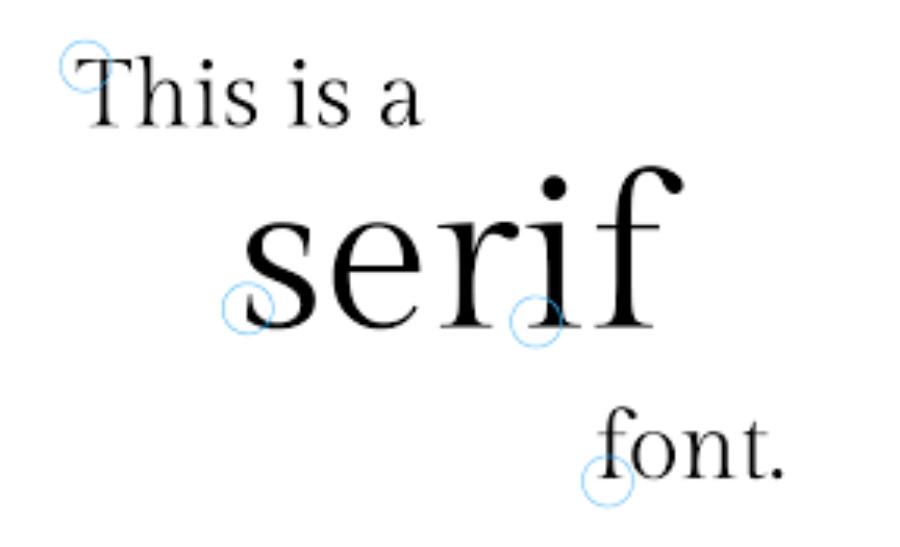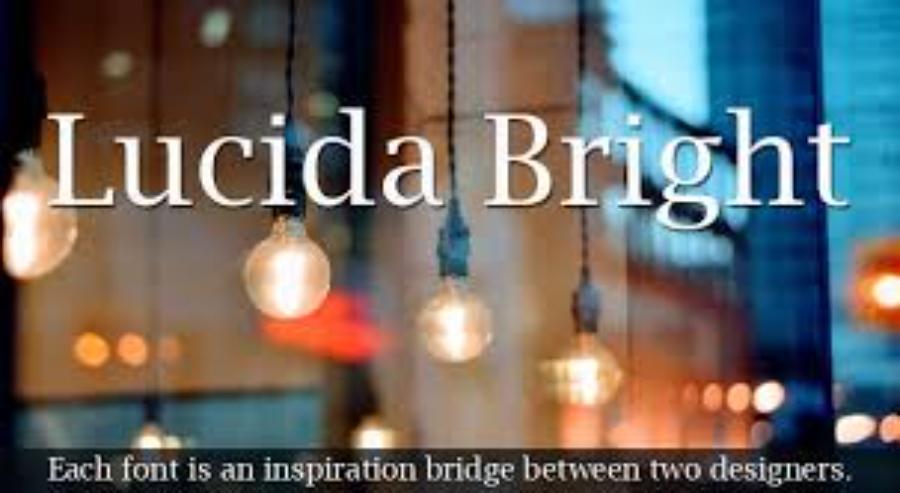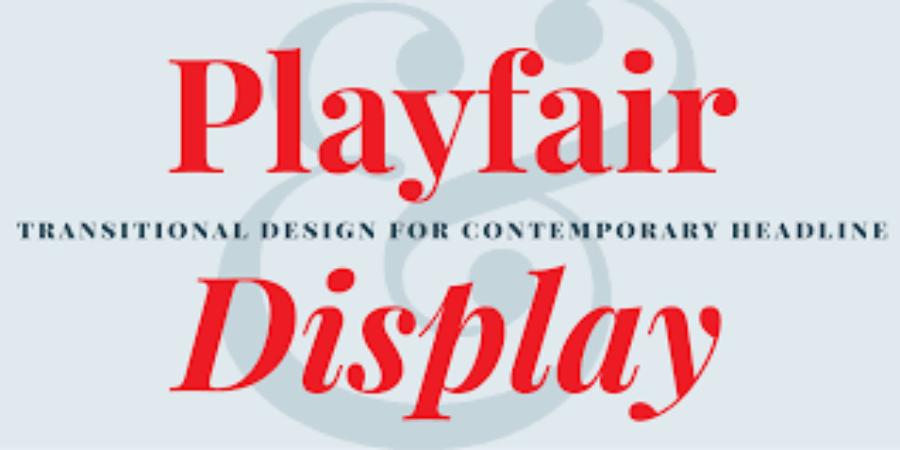
Danh sách 20 Font Chữ Đẳng Cấp Mà Designer Nên Sở Hữu Ngay Hôm Nay
Khám phá 20 fonts chữ sang trọng dành cho designer. Cập nhật bộ sưu tập các font chữ đẳng cấp để nâng tầm thiết kế của bạn, từ phong cách hiện đại đến cổ điển.
Khi thiết kế đồ họa, lựa chọn font chữ đóng vai trò vô cùng quan trọng trong việc tạo ra những ấn phẩm nổi bật. Một font chữ sang trọng không chỉ giúp nâng cao giá trị thẩm mỹ mà còn thể hiện được sự chuyên nghiệp và tinh tế của nhà thiết kế. Trong bài viết này, sadesign sẽ giới thiệu 20 fonts chữ sang trọng mà mọi designer đều nên có trong bộ sưu tập của mình, giúp các bạn dễ dàng lựa chọn những kiểu chữ phù hợp với từng dự án.
1. Serif - Một Biểu Tượng Của Sự Sang Trọng
Serif là một trong những loại font chữ cổ điển và thường xuyên xuất hiện trong các thiết kế mang tính trang trọng. Với các chân chữ được nối vào phần thân, Serif tạo ra một cảm giác chắc chắn và dễ đọc, đặc biệt phù hợp với những thiết kế cần sự trang nghiêm và lịch sự. Những font như Times New Roman, Georgia, hay Baskerville đều là những ví dụ điển hình cho thể loại này.
Serif luôn được coi là biểu tượng của sự sang trọng và tinh tế trong thiết kế đồ họa. Với đường nét mềm mại, cân đối và đầy tính nghệ thuật, các font chữ Serif không chỉ giúp tăng tính thẩm mỹ mà còn mang lại cảm giác chuyên nghiệp và đẳng cấp cho các dự án thiết kế. Việc lựa chọn đúng font chữ Serif phù hợp có thể tạo nên sự khác biệt lớn, giúp truyền tải thông điệp một cách hiệu quả và gây ấn tượng mạnh mẽ với người xem. Vì vậy, việc khám phá và sử dụng những font chữ sang trọng này là điều mà các nhà thiết kế không nên bỏ qua để nâng tầm giá trị cho sản phẩm của mình.
2. Didot - Sự Tinh Tế Của Font Chữ Sang Trọng
Didot là một font chữ serif nổi bật, nổi bật với các nét thanh mảnh nhưng không kém phần mạnh mẽ. Nó được biết đến với vẻ đẹp thanh lịch và đẳng cấp, lý tưởng cho các thiết kế trong ngành thời trang, làm đẹp, hoặc các sản phẩm cao cấp. Với tỷ lệ tương phản mạnh mẽ giữa các nét chữ, Didot mang đến một phong cách cổ điển nhưng vô cùng hiện đại.
Với sự kết hợp hoàn hảo giữa các đường nét thanh mảnh và độ tương phản cao, Didot mang lại cảm giác hiện đại nhưng vẫn giữ được vẻ cổ điển đặc trưng. Đây là lựa chọn lý tưởng cho các dự án cần thể hiện sự đẳng cấp và tinh tế, từ thiết kế thương hiệu, in ấn cao cấp đến các ấn phẩm thời trang. Sự cân đối trong từng chi tiết của Didot không chỉ tạo ấn tượng mạnh mẽ về mặt thẩm mỹ mà còn giúp nâng tầm giá trị của sản phẩm thiết kế.
3. Bodoni - Cổ Điển Nhưng Vẫn Mới Mẻ
Bodoni là một font chữ serif khác sở hữu nét đẹp quý phái, trang trọng. Được ra đời từ thế kỷ 18, Bodoni có sự kết hợp giữa các đường nét đậm và mảnh tạo ra một hiệu ứng thẩm mỹ rất đặc biệt. Đây là font chữ lý tưởng cho các thiết kế mang tính chất cao cấp như các ấn phẩm văn hóa, sách hay các chiến dịch quảng cáo của thương hiệu lớn.
4. Futura - Đơn Giản Nhưng Vẫn Sang Trọng
Futura là một font chữ sans-serif với các đường nét đơn giản nhưng không kém phần sang trọng. Nhờ vào thiết kế hiện đại và gọn gàng, Futura dễ dàng được áp dụng trong nhiều loại thiết kế, từ logo đến các ấn phẩm truyền thông. Đây là một trong những font chữ phổ biến mà bất kỳ designer nào cũng nên có.
5. Helvetica - Đỉnh Cao Của Sự Hoàn Hảo
Helvetica là một trong những font chữ phổ biến nhất trên thế giới. Sự đơn giản, thanh thoát và dễ đọc của Helvetica khiến nó trở thành sự lựa chọn hoàn hảo cho các thiết kế sang trọng. Dù là trong các dự án thương mại hay nghệ thuật, Helvetica đều mang đến sự tinh tế không thể phủ nhận.
6. Montserrat - Đường Nét Mạnh Mẽ và Tinh Tế
Montserrat là một font chữ sans-serif với thiết kế mạnh mẽ và hiện đại, nhưng vẫn giữ được sự thanh thoát, dễ chịu khi sử dụng. Font chữ này phù hợp cho các thiết kế quảng cáo, website, và các dự án cần sự chuyên nghiệp và nổi bật.
7. Playfair Display - Sự Kết Hợp Giữa Cổ Điển và Hiện Đại
Nếu bạn tìm kiếm một font chữ vừa mang phong cách cổ điển, vừa đậm chất hiện đại, Playfair Display là một lựa chọn lý tưởng. Với những đường nét mềm mại và thanh thoát, font chữ này đặc biệt phù hợp cho các thiết kế nội dung cao cấp như tạp chí, sách, hoặc các chiến dịch truyền thông cho thương hiệu.
8. Raleway - Tinh Tế Và Sang Trọng
Raleway là một font chữ sans-serif với các đường nét mỏng nhẹ và sắc nét. Với nhiều kiểu chữ khác nhau, Raleway mang đến sự linh hoạt trong việc sử dụng, đồng thời vẫn giữ được tính sang trọng cần thiết cho các thiết kế cao cấp.
9. Garamond - Lịch Lãm Và Đẳng Cấp
Garamond là một trong những font chữ lâu đời và có tính lịch lãm vượt thời gian. Với các đường cong mềm mại và thanh thoát, Garamond rất phù hợp cho những thiết kế yêu cầu sự sang trọng và trang nhã như các ấn phẩm in ấn, sách, và các tài liệu doanh nghiệp.
10. Lora - Tính Sang Trọng Trong Mỗi Đường Nét
Lora là một font chữ serif với các đường cong thanh thoát, dễ đọc và vô cùng sang trọng. Lora thích hợp cho những thiết kế cần tạo ra cảm giác tinh tế, từ các bài viết đến các sản phẩm thiết kế quảng cáo.
11. Avenir - Tương Lai Của Font Chữ Sang Trọng
Avenir là một font chữ sans-serif, nổi bật với những đường nét hiện đại nhưng không kém phần thanh thoát. Đây là một lựa chọn tuyệt vời cho các thiết kế cần sự tối giản nhưng vẫn đầy tinh tế, đặc biệt là trong các sản phẩm công nghệ hay thiết kế website.
12. Century Gothic - Tinh Tế Và Đơn Giản
Với những đường nét tròn trịa và dễ chịu, Century Gothic mang đến một vẻ ngoài hiện đại và sang trọng. Font chữ này rất phù hợp cho các thiết kế cần sự thanh thoát và dễ đọc, chẳng hạn như các thiết kế logo, banner hay quảng cáo trực tuyến.
13. Courier New - Cảm Hứng Từ Thời Gian Cổ Điển
Courier New mang một vẻ đẹp cổ điển với các đường nét chữ rõ ràng và mạnh mẽ. Mặc dù có thiết kế đơn giản, font chữ này vẫn tạo ra một không gian sang trọng và đáng tin cậy, rất thích hợp cho các thiết kế in ấn cổ điển hay các sản phẩm yêu cầu sự nghiêm túc.
14. Tisa - Sự Lựa Chọn Cho Tính Sang Trọng Mềm Mại
Tisa là một font chữ serif với sự kết hợp giữa sự mềm mại và tính sắc nét. Font chữ này mang đến cảm giác ấm áp, gần gũi nhưng không kém phần sang trọng, phù hợp cho các thiết kế in ấn và các ấn phẩm truyền thông cao cấp.
15. Museo - Tinh Tế và Hiện Đại
Museo là một font chữ serif hiện đại với các đường nét đầy đặn và dễ đọc. Font chữ này mang đến sự thanh lịch và nổi bật, rất thích hợp cho các thiết kế website hoặc các ấn phẩm quảng cáo có yêu cầu sự chuyên nghiệp.
16. Lucida Bright - Sự Kết Hợp Giữa Sang Trọng Và Dễ Đọc
Lucida Bright là một font chữ serif dễ đọc với những đường cong thanh thoát, thích hợp cho các thiết kế cần sự sang trọng và dễ tiếp cận. Với thiết kế tinh tế, đường nét mềm mại nhưng vẫn giữ được sự rõ ràng, Lucida Bright mang lại cảm giác chuyên nghiệp và đẳng cấp cho các dự án thiết kế. Đây là phông chữ lý tưởng để sử dụng trong các tài liệu in ấn, thiết kế thương hiệu, hoặc các dự án đòi hỏi sự chú trọng đến chi tiết và thẩm mỹ cao. Nhà thiết kế không nên bỏ qua Lucida Bright nếu muốn tạo nên những sản phẩm vừa bắt mắt vừa dễ tiếp cận.
17. Poppins - Sự Kết Hợp Hoàn Hảo Giữa Tinh Tế Và Hiện Đại
Poppins là một font chữ sans-serif hiện đại với các đường nét mảnh mai và dễ dàng sử dụng trong mọi loại thiết kế. Nó mang lại cảm giác trẻ trung, nhưng vẫn thể hiện được sự sang trọng và chuyên nghiệp.
18. Exo 2 - Tối Giản Nhưng Sang Trọng
Exo 2 là một font chữ sans-serif có thiết kế hiện đại với những đường nét sắc nét. Font chữ này rất phù hợp cho các thiết kế công nghệ, truyền thông hiện đại, giúp các sản phẩm của bạn trở nên nổi bật và thu hút.
Với đường nét hiện đại và linh hoạt, Exo 2 không chỉ phù hợp cho các dự án thiết kế cao cấp mà còn mang lại cảm giác chuyên nghiệp và đẳng cấp. Đây chính là lựa chọn lý tưởng để tạo điểm nhấn cho thương hiệu, ấn phẩm hoặc giao diện người dùng, giúp truyền tải thông điệp một cách hiệu quả và đầy ấn tượng.
19. Oswald - Đơn Giản Nhưng Đầy Mạnh Mẽ
Oswald là một font chữ sans-serif với các đường nét mạnh mẽ và dễ đọc. Nó được sử dụng phổ biến trong các thiết kế cần sự đột phá và mạnh mẽ mà vẫn giữ được sự sang trọng cần thiết.
20. Merriweather - Sang Trọng Trong Mỗi Chữ Cái
Merriweather là một font chữ serif có sự kết hợp hoàn hảo giữa sự dễ đọc và vẻ đẹp trang nhã. Font chữ này rất thích hợp cho các thiết kế in ấn, sách hay các sản phẩm quảng cáo cần sự sang trọng và dễ tiếp cận.
Merriweather là một trong những font chữ sang trọng mà bất kỳ designer nào cũng không nên bỏ qua. Với thiết kế tinh tế, từng đường nét của Merriweather đều toát lên sự đẳng cấp và chuyên nghiệp, phù hợp cho nhiều dự án sáng tạo như thiết kế thương hiệu, ấn phẩm in ấn hay giao diện số. Font chữ này không chỉ mang lại tính thẩm mỹ cao mà còn đảm bảo khả năng đọc dễ dàng, giúp truyền tải thông điệp một cách hiệu quả. Nếu bạn đang tìm kiếm một font chữ vừa hiện đại vừa lịch lãm, Merriweather chắc chắn sẽ là sự lựa chọn hoàn hảo.
21. Kết bài
Việc lựa chọn font chữ đúng không chỉ là sự kết hợp giữa tính thẩm mỹ và sự dễ đọc mà còn phải phù hợp với thông điệp mà bạn muốn truyền tải trong mỗi dự án thiết kế. 20 font chữ sang trọng mà chúng tôi đã giới thiệu sẽ là công cụ tuyệt vời để giúp bạn tạo nên những tác phẩm thiết kế nổi bật và đẳng cấp. Hãy thử nghiệm và tìm ra những font chữ phù hợp nhất để nâng tầm công việc thiết kế của bạn.